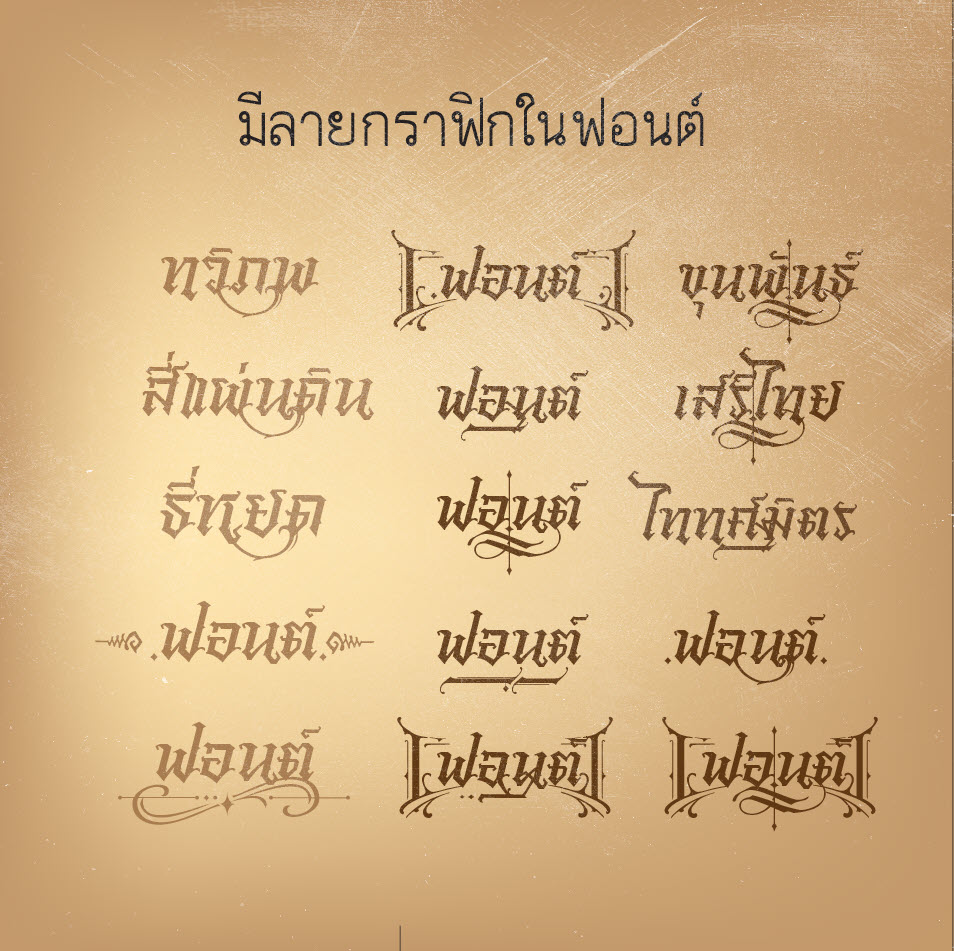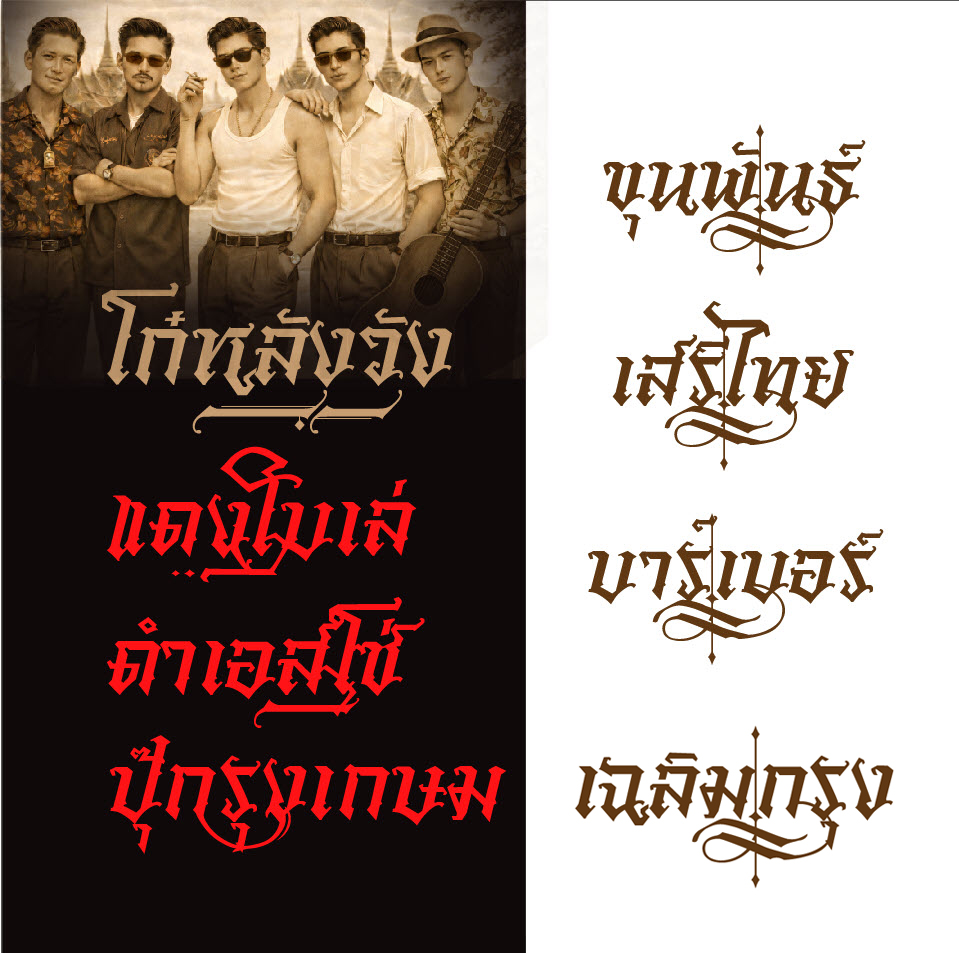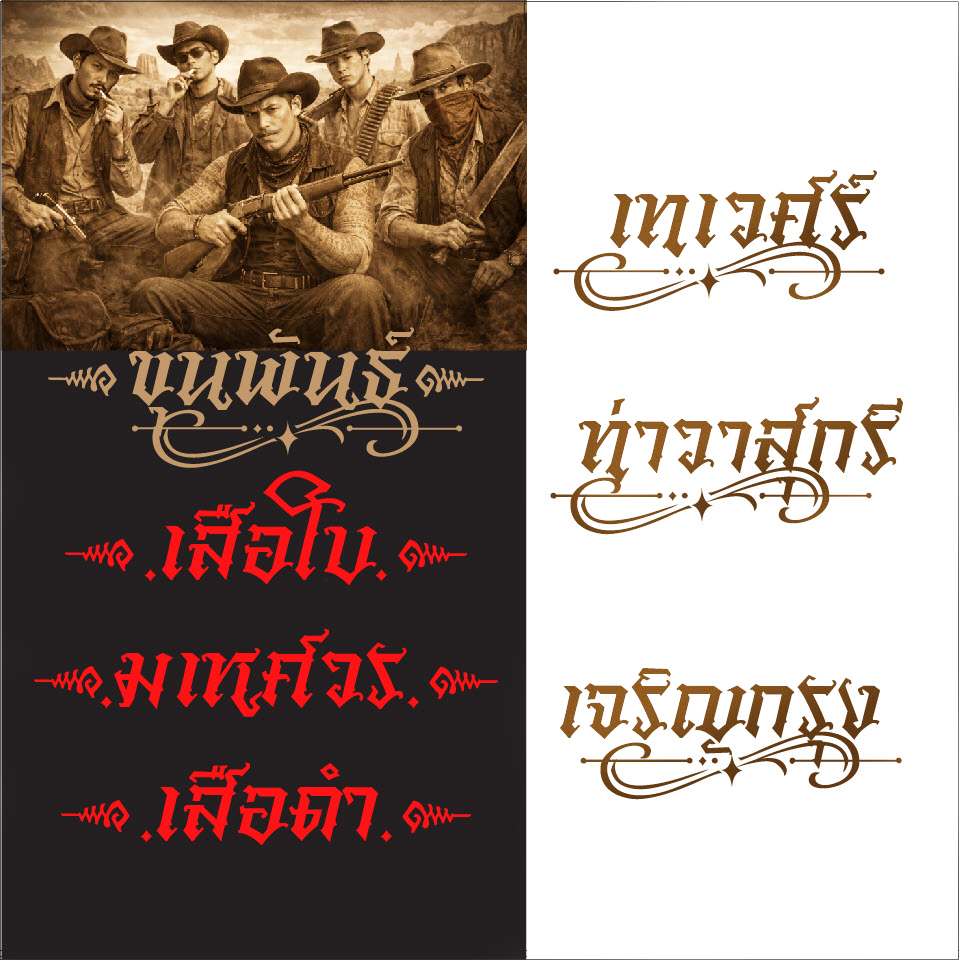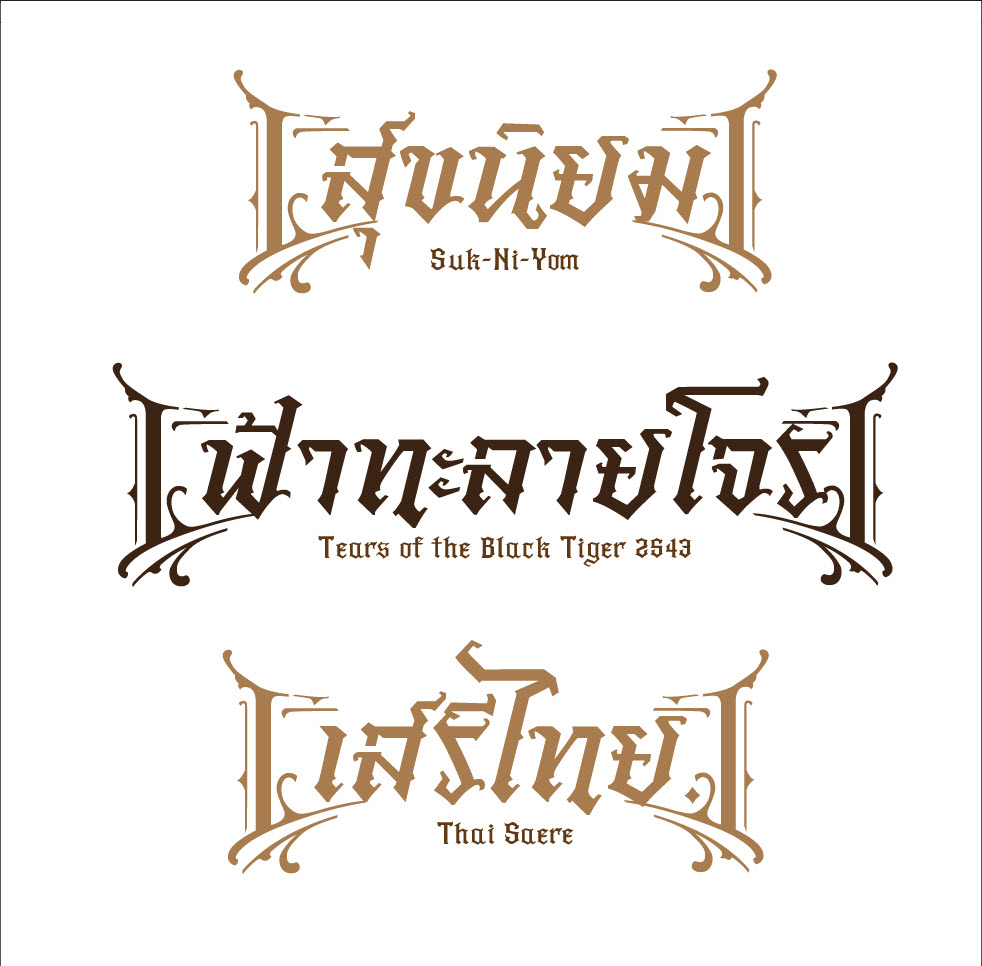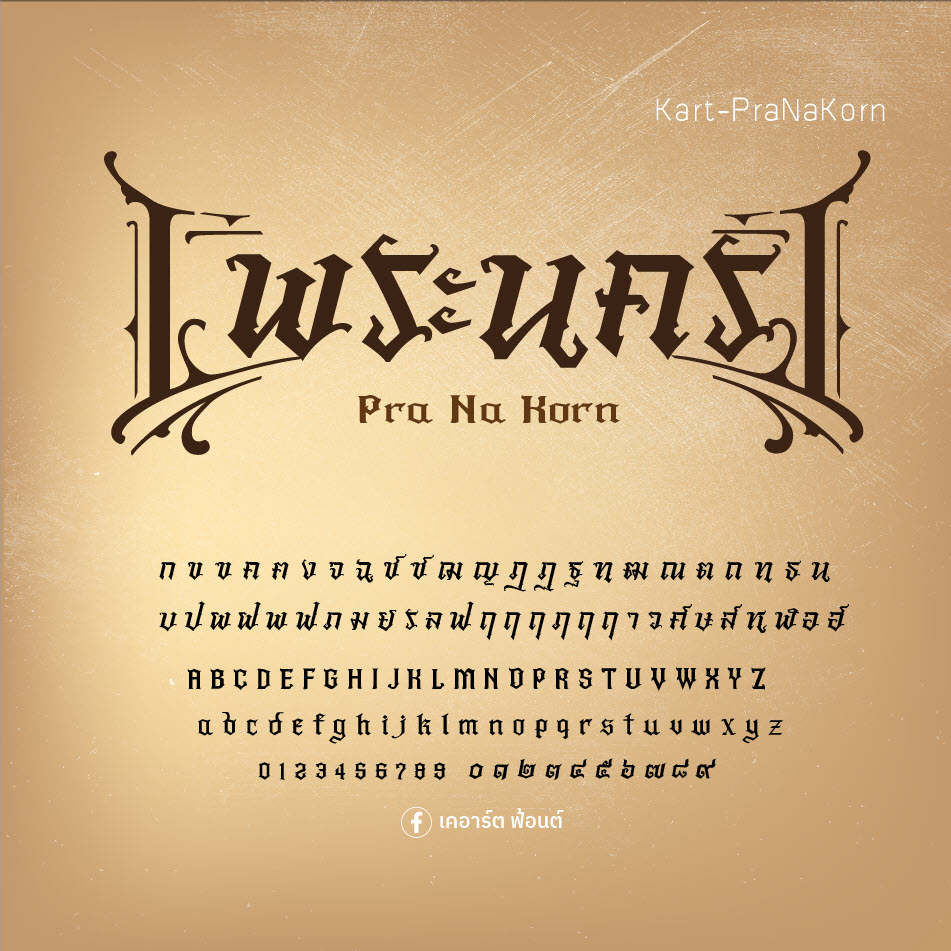
- ฟอนต์ CkNobel ฟอนต์ลายมือแนวหัวกลมโต น่ารักอ่านง่ายแบบวัยรุ่นค่ะ
ฟอนต์ เคอาร์ต-พระนคร (Kart-PranaKorn ) เป็นฟอนต์ที่เขียนอยากให้เป็น #ฟอนต์ย้อนยุค #ฟอนต์ไทยวินเทจ ย้อนยุค แบบสมัยก่อน ฟอนต์นี้มีลายกราฟิกอยู่ในฟอนต์ครับ   เป็นเดโม่ครับ สามารถใช้ครอบคลุมหลายโปรแกรมโหลดทดลอง กับไอแพด และแอนดรอยด์ดูก่อนได้ สนับสนุนผลงงานแบบเต็มพร้อมใบรับรองสิทธิ์ใช้งานเชิงพาณิชย์ตลอดชีพ สนับสนุนได้ 300 บาทครับ